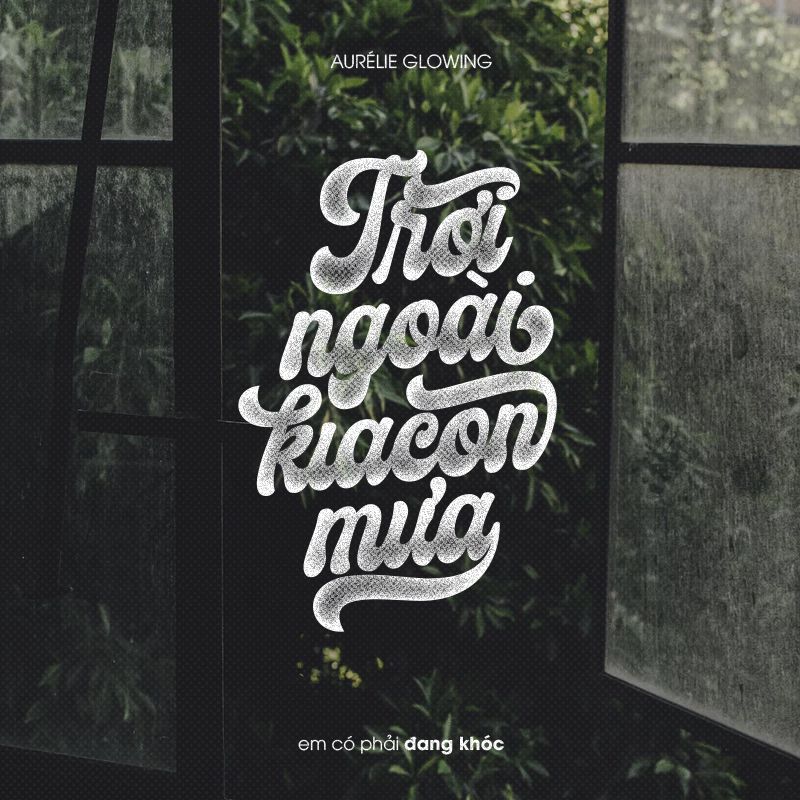
[ SHARE #02 ] FONT KH GINCHIEST REGULAR
Font này thì xinh khỏi nói, nhiều glyphs, lại còn đã được mình việt hoá rồi, các bạn cứ an tâm sử dụng nhaaaaa.